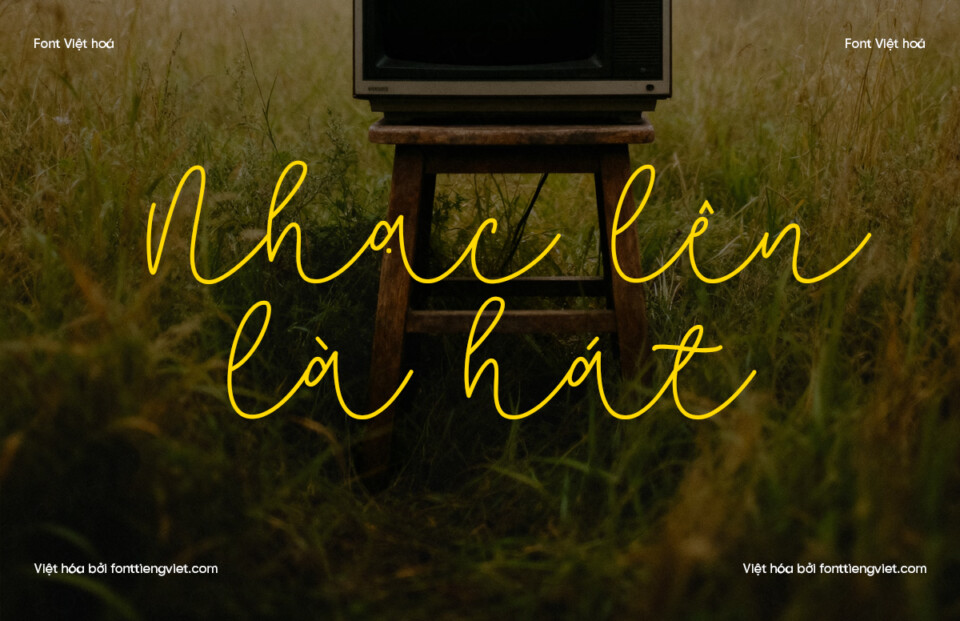
Font Việt hóa 1FTV VIP Snowy Dream Script
Giới thiệu về bộ Font Việt hóa 1FTV VIP Snowy Dream Script
Trong thế giới đồ họa hiện đại, việc tìm kiếm một bộ Font Miễn Phí chất lượng và đầy đủ dấu tiếng Việt luôn là ưu tiên hàng đầu của các nhà sáng tạo. Font Việt hóa 1FTV VIP Snowy Dream Script nổi lên như một hiện tượng nhờ phong cách thiết kế uyển chuyển, mang đậm hơi thở nghệ thuật chữ viết tay. Đây là một phông chữ dạng script với các đường nét thanh mảnh nhưng vô cùng sắc sảo, gợi lên cảm giác về những giấc mơ tuyết trắng đầy thơ mộng và tinh khôi. Bộ phông này không chỉ đơn thuần là các ký tự mà còn là một tác phẩm nghệ thuật giúp truyền tải cảm xúc mạnh mẽ đến người xem ngay từ cái nhìn đầu tiên.
Những đặc điểm nổi bật của Font Việt hóa 1FTV VIP Snowy Dream Script
Phong cách thiết kế thanh lịch và hiện đại
Font Việt hóa 1FTV VIP Snowy Dream Script sở hữu cấu trúc chữ nghiêng nhẹ nhàng, tạo ra sự nhịp điệu tự nhiên như nét bút lông trên mặt giấy. Các ký tự được kết nối với nhau một cách khéo léo, tạo nên tổng thể hài hòa và đồng nhất. Điều này giúp bộ font trở nên cực kỳ phù hợp cho các dự án đòi hỏi tính thẩm mỹ cao, từ thiệp cưới, bìa sách đến các ấn phẩm quảng cáo cao cấp. Độ dày của nét chữ được tính toán kỹ lưỡng để đảm bảo tính dễ đọc ngay cả khi sử dụng ở kích thước nhỏ, giúp các nhà thiết kế tự tin áp dụng vào nhiều loại sản phẩm khác nhau mà không lo bị rối mắt.
Khả năng tương thích và tối ưu hóa tiếng Việt
Điểm giá trị nhất của phiên bản này chính là việc đã được đội ngũ chuyên gia tối ưu hóa hoàn toàn cho bảng mã tiếng Việt. Người dùng sẽ không còn gặp phải các lỗi hiển thị dấu hay khoảng cách ký tự không đều thường thấy ở các bản font gốc chưa qua chỉnh sửa. Font Việt hóa 1FTV VIP Snowy Dream Script hỗ trợ đầy đủ các ký tự đặc biệt và dấu thanh của tiếng Việt, giúp văn bản trở nên chuyên nghiệp và chỉn chu hơn. Sự kết hợp giữa vẻ đẹp ngoại hình và sự tiện dụng về mặt kỹ thuật đã biến nó trở thành một công cụ không thể thiếu trong kho tài nguyên của bất kỳ designer nào tại Việt Nam hiện nay.
Ứng dụng thực tế của Font Việt hóa 1FTV VIP Snowy Dream Script
Với vẻ ngoài sang trọng, bộ font này thường được ưu tiên sử dụng trong lĩnh vực thiết kế thương hiệu và bao bì sản phẩm. Bạn có thể dễ dàng bắt gặp những logo hay slogan sử dụng Font Việt hóa 1FTV VIP Snowy Dream Script trên các sản phẩm mỹ phẩm, thời trang hoặc đồ thủ công mỹ nghệ. Ngoài ra, trong môi trường giáo dục, giáo viên và học sinh cũng có thể sử dụng phông chữ này để trang trí các bài thuyết trình, thiệp chúc mừng hoặc làm tiêu đề cho các báo cáo sáng tạo. Sự linh hoạt này giúp bộ font tiếp cận được nhiều đối tượng người dùng, từ những người chuyên nghiệp đến những bạn trẻ mới bắt đầu làm quen với lĩnh vực thiết kế đồ họa cơ bản.